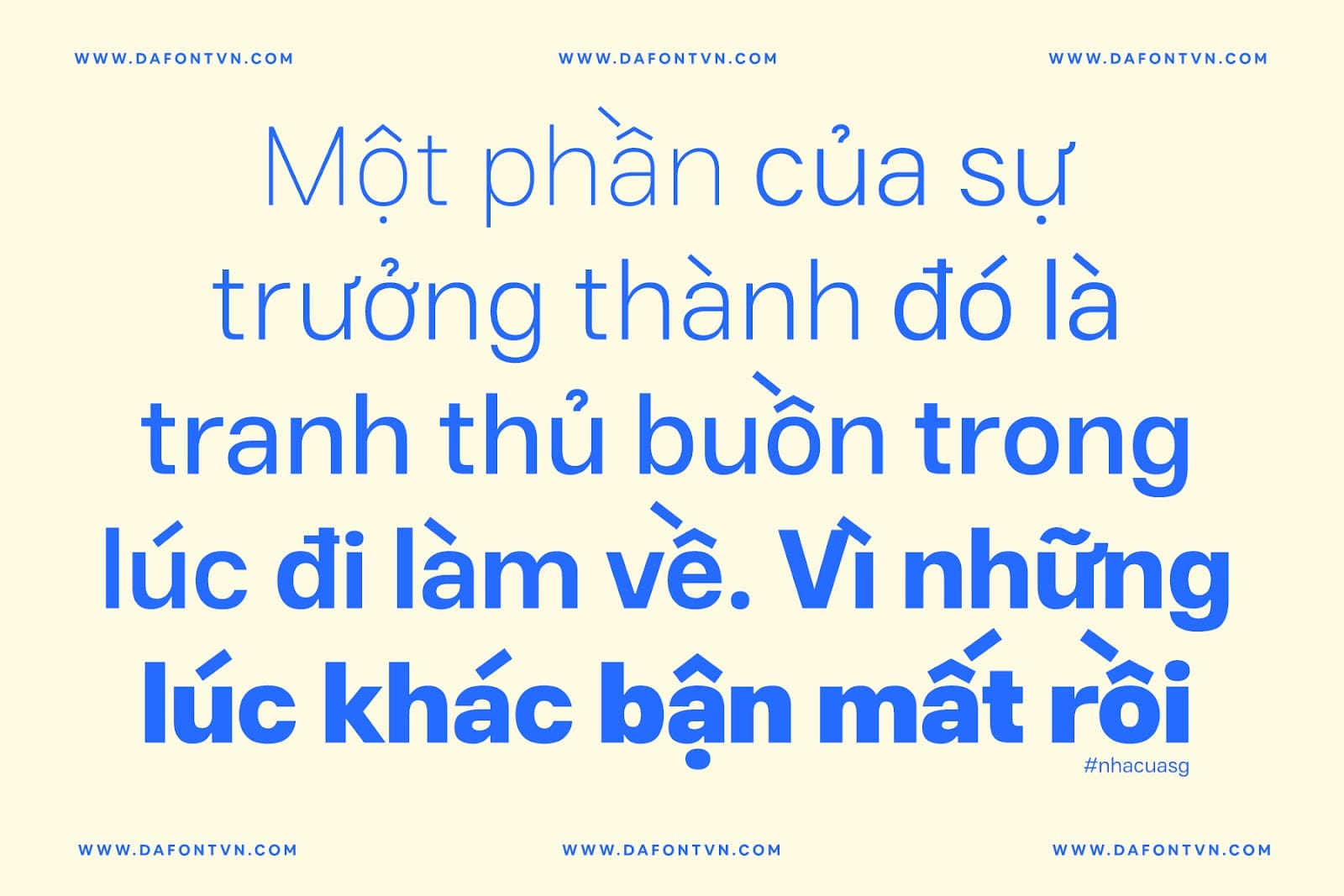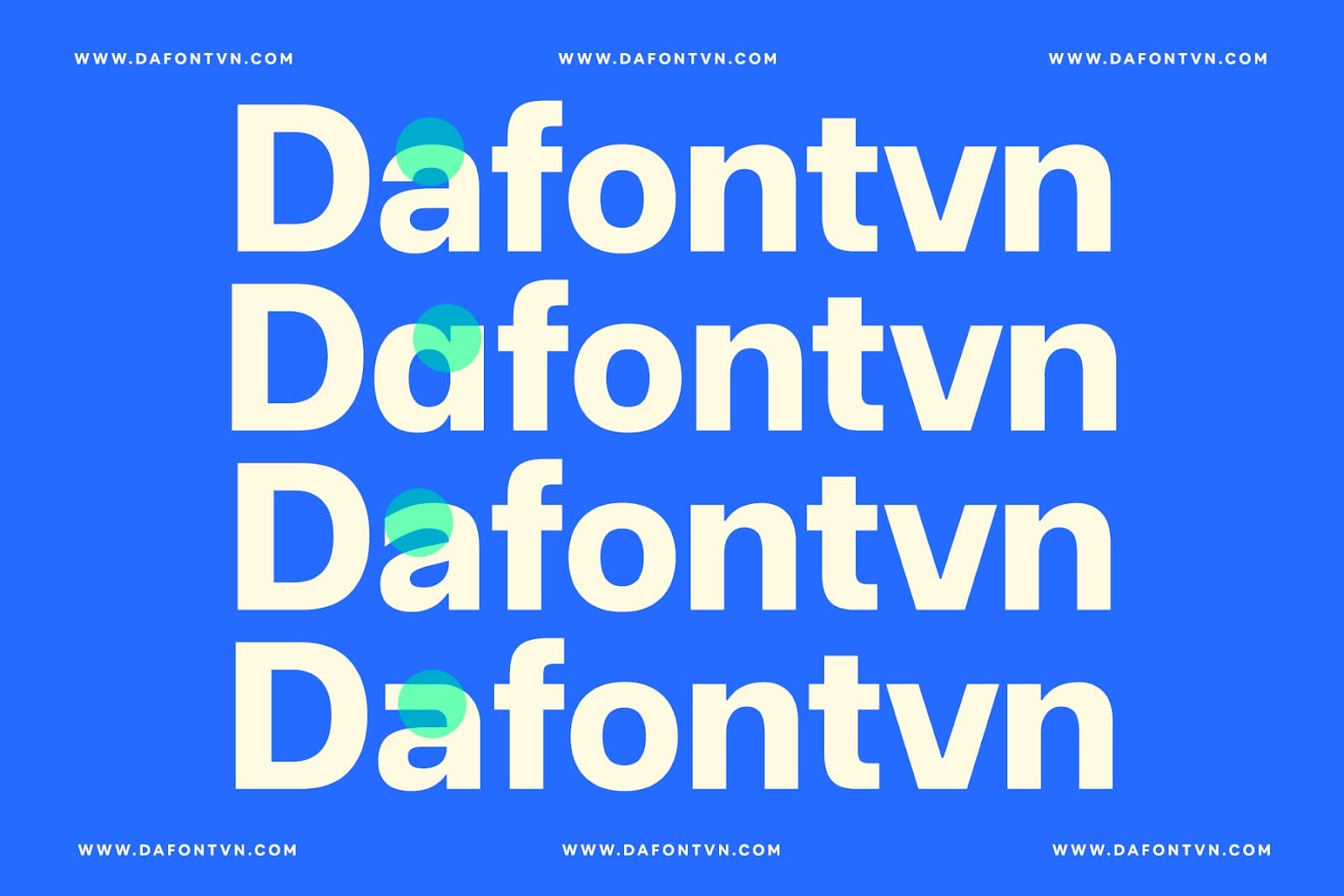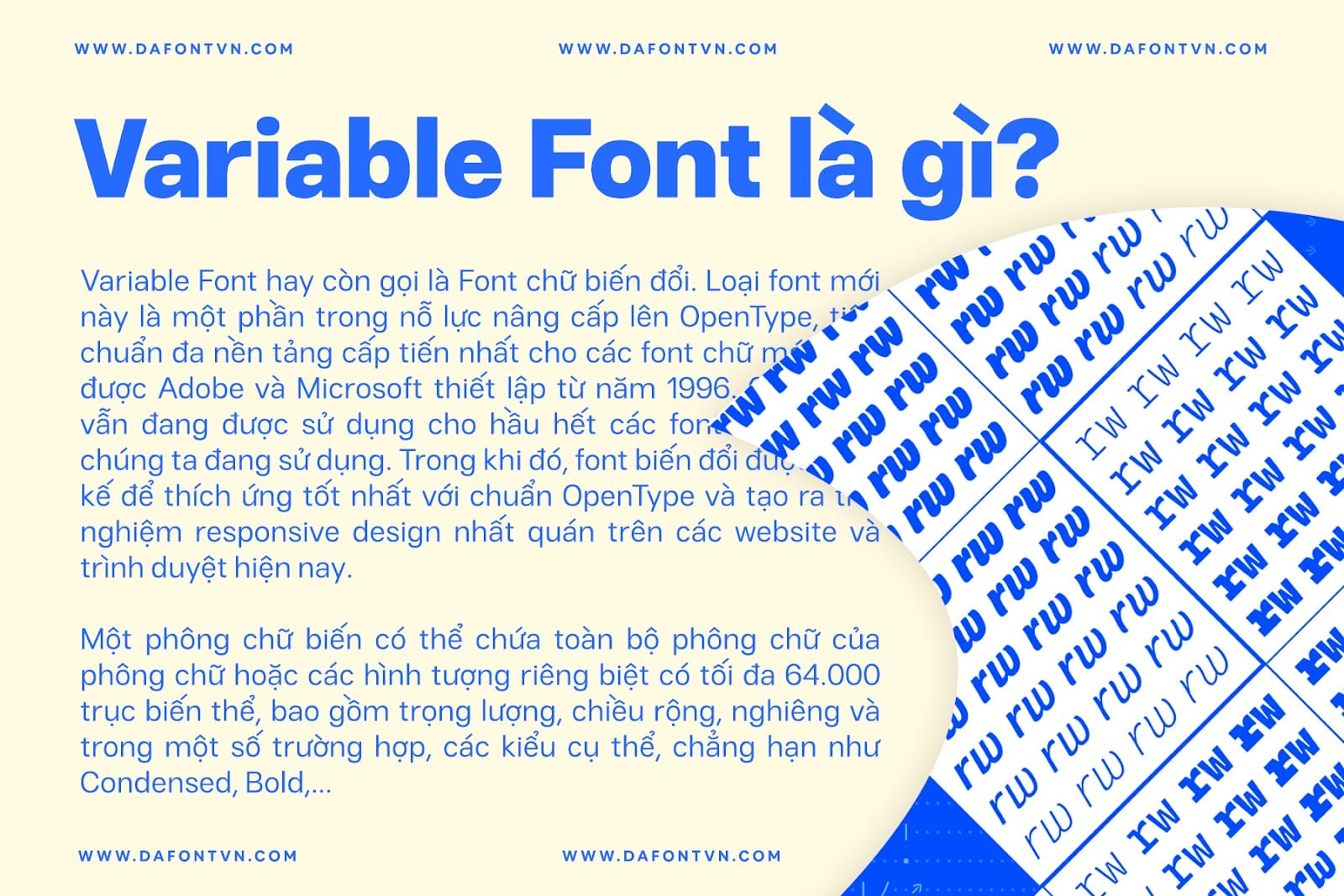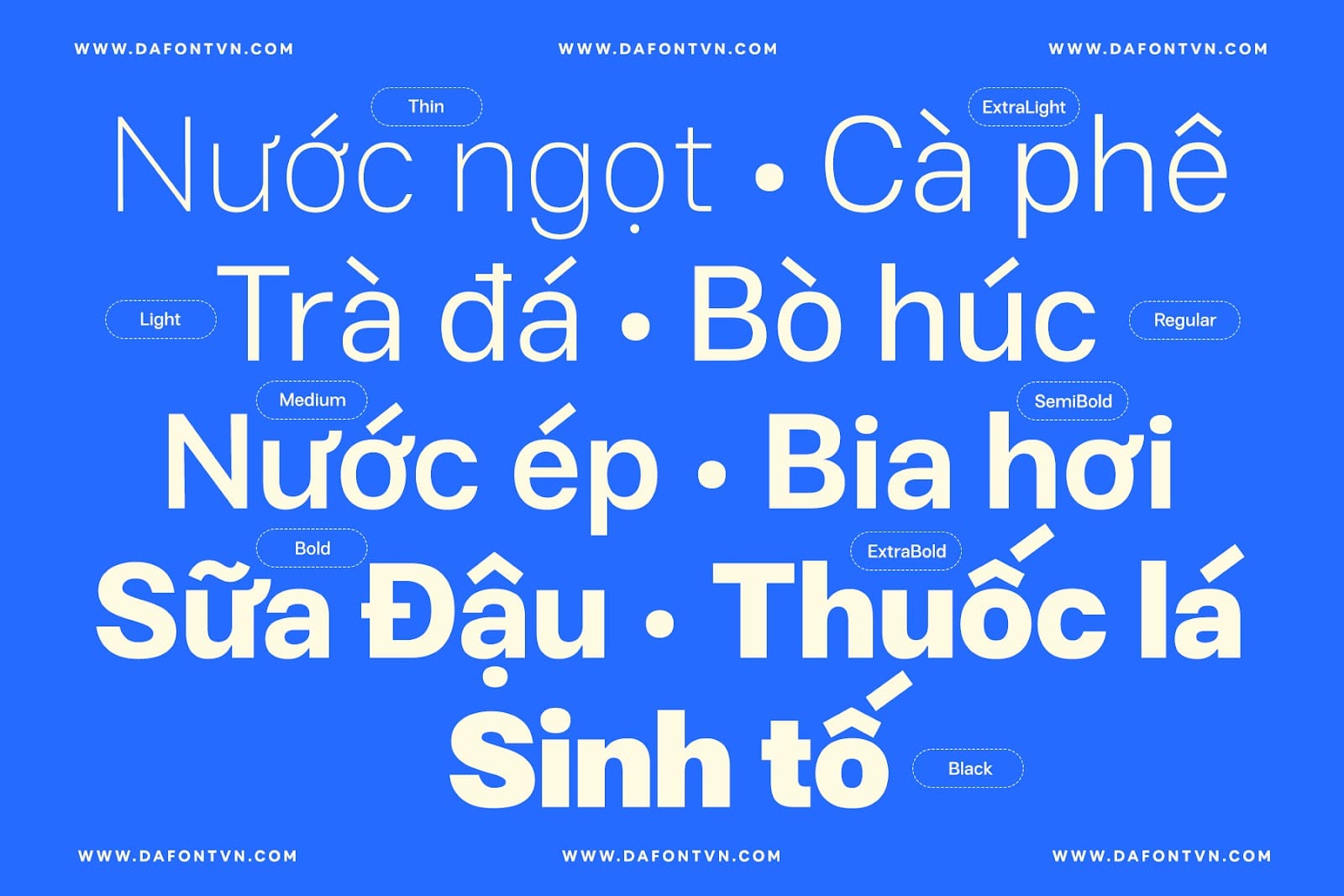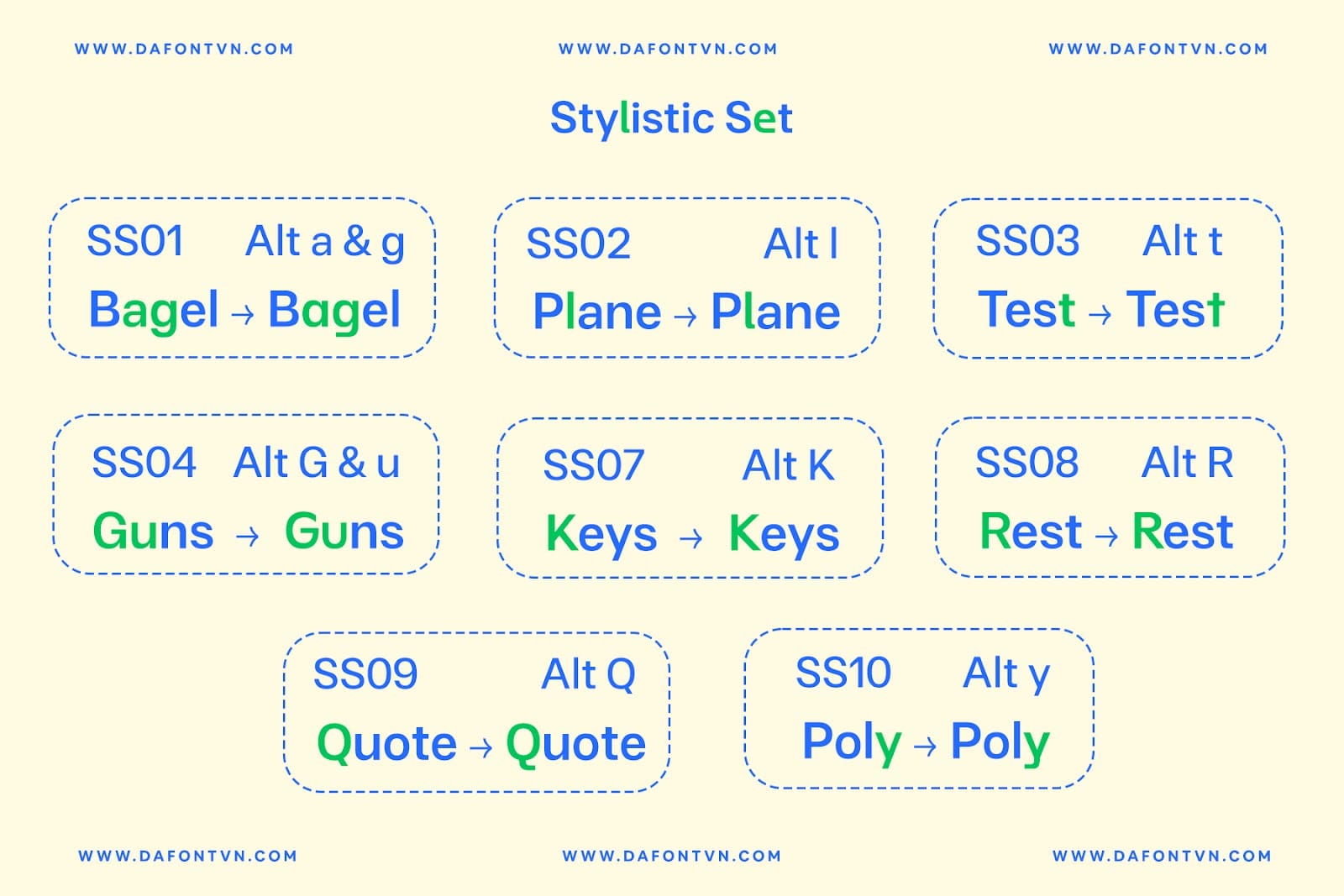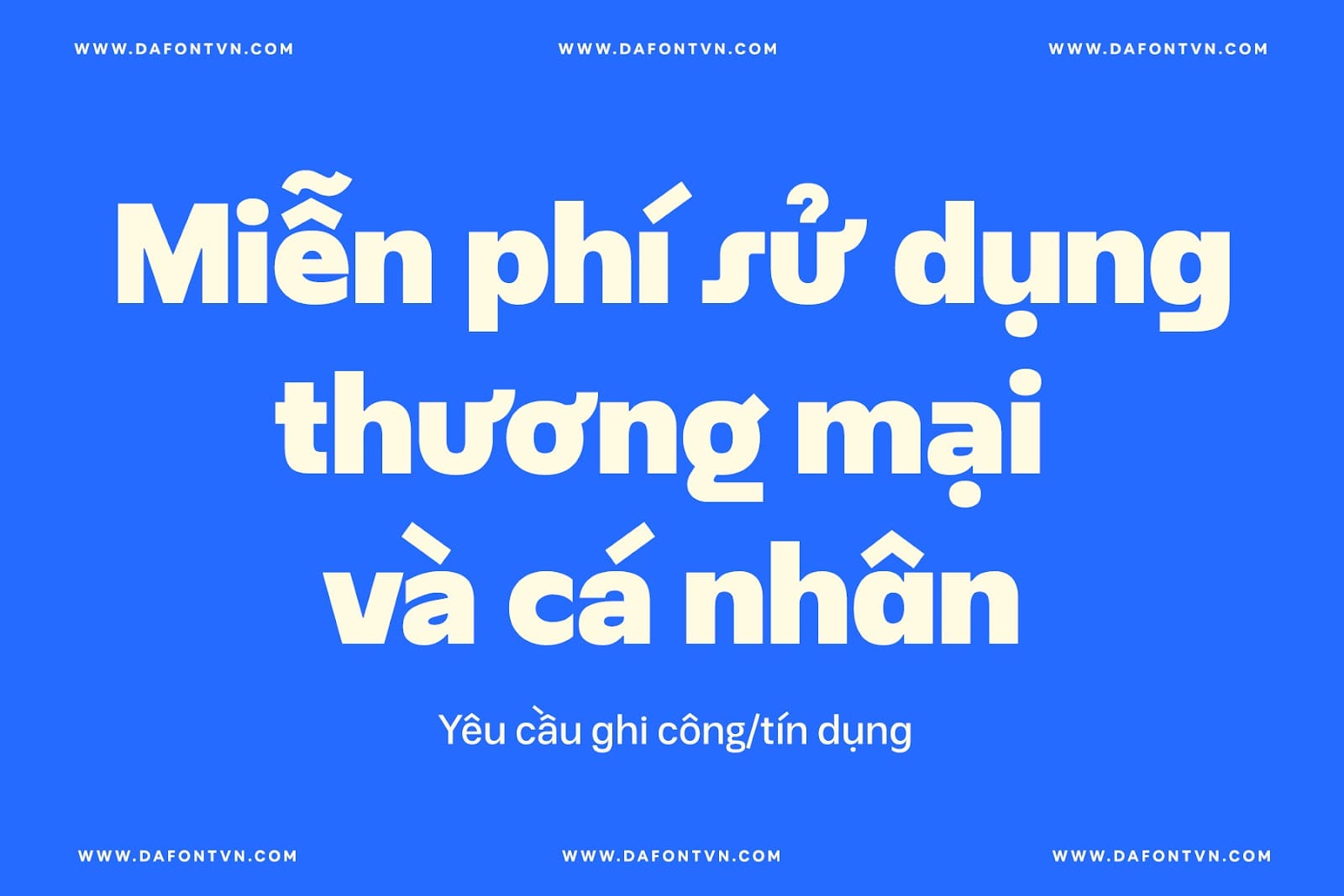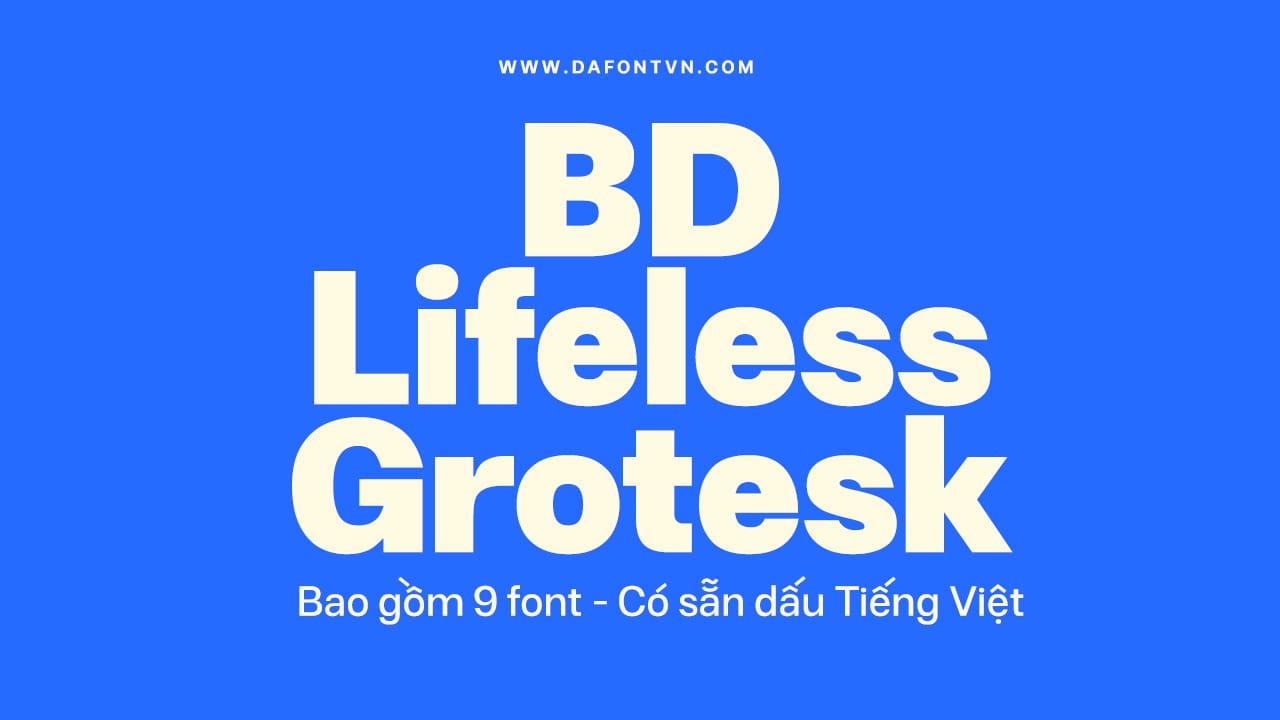
BD Lifeless Grotesk là bộ font tiếng Việt bao gồm 9 kiểu được thiết kế bởi tác giả Harry Dinh và được chia sẻ miễn phí. Hiện tại đây chỉ đang là phiên bản beta tuy nhiên bộ font gần như hoàn chỉnh và phiên bản in nghiêng sẽ được ra mắt trong thời gian tới.Đây là bộ font vô cùng chất lượng và đẹp mắt bạn có thể sử dụng nó cho nhiều thiết kế và được hiển thị rất tốt ở nhiều các kích thước khác nhau như tiêu đề, văn bản. Ngoài ra font chữ còn bao gồm rất nhiều biến thể với các ký tự khác nhau để bạn có thể thay đổi kiểu chữ cho ấn tượng hơn.